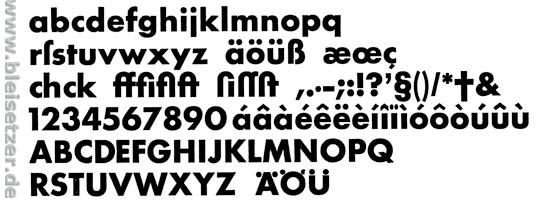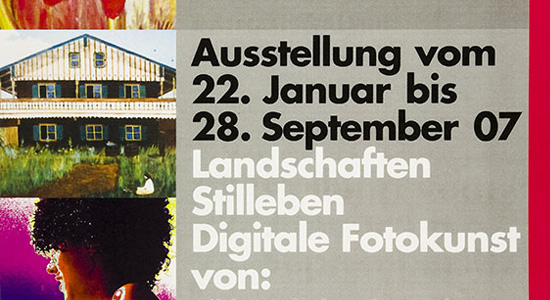
Serifenlos und spitz. Vor 30 oder 40 Jahren öfter gesehen.
Hallo zunächst einmal. Ich bin neu hier. Ich suche aus purem Interesse den Namen der Schrift auf diesem Plakat. Gestaltet wurde es vom Grafik-Studio Gogolin (Bayrischzell).
Bauersche Gießerei, Frankfurt am Main
Erstguß 1927
Paul Renner
Schau mal, was für hübsche Ligaturen diese Schrift hat.
Übrigens - weil Du "spitz" schreibst: Die Futura Buchschrift, die der Normal-Version entspricht, hat tatsächlich ein spitz zulaufendes Versal-A.